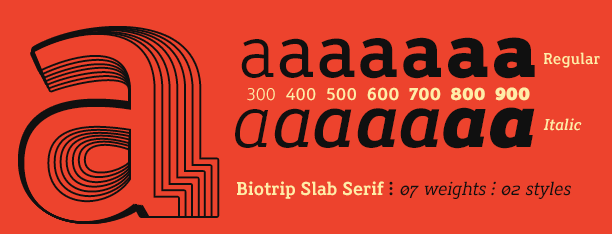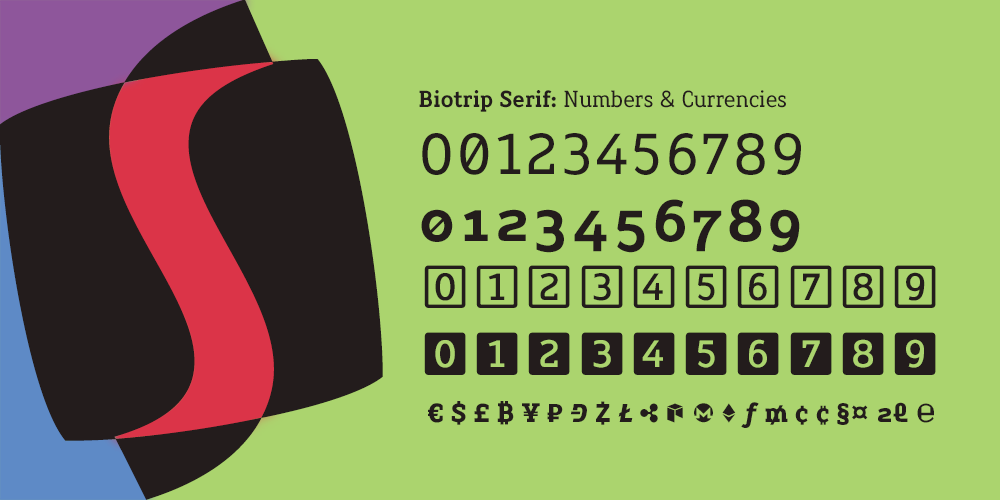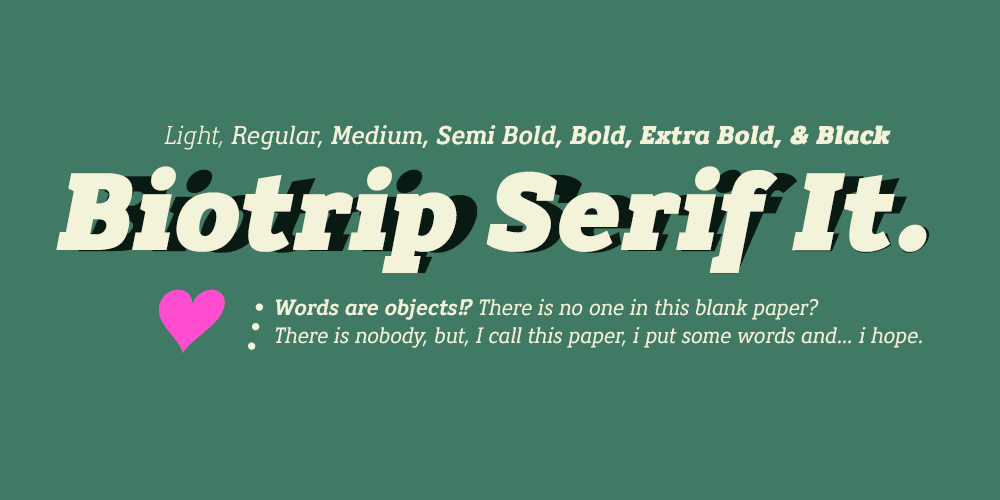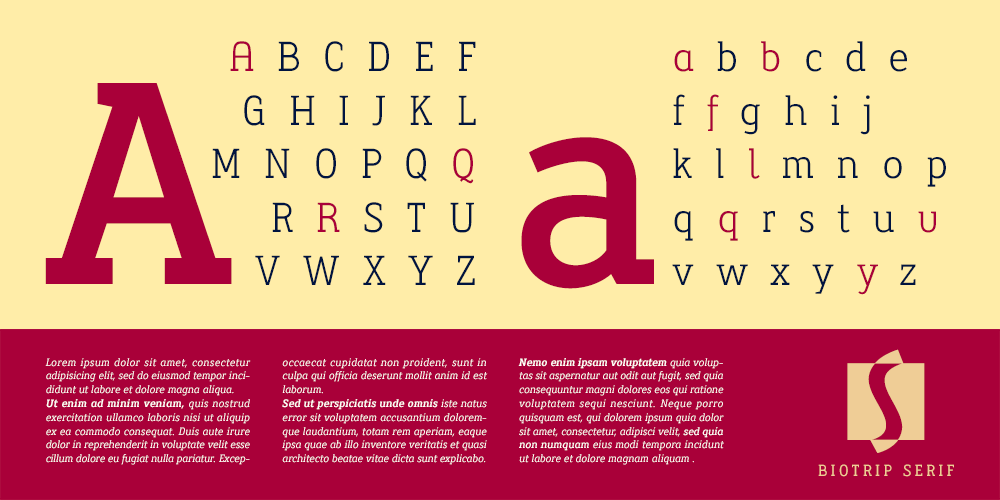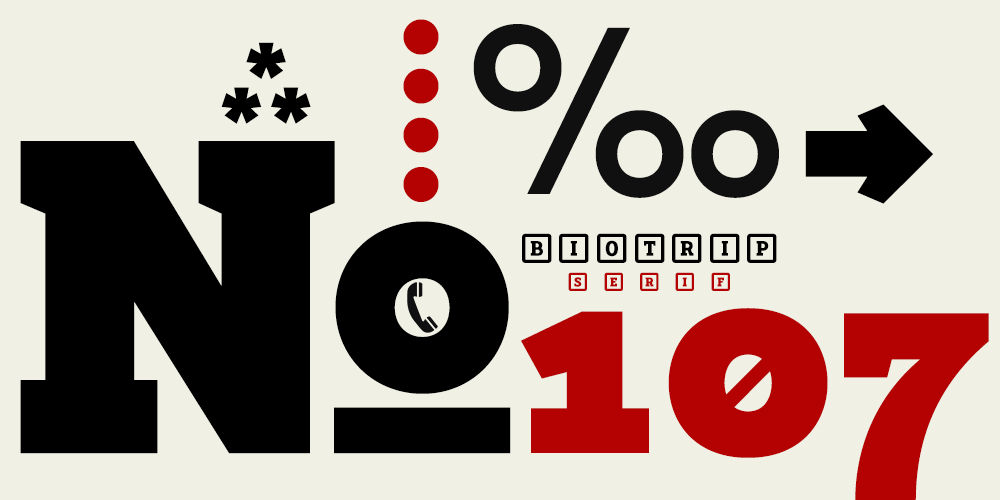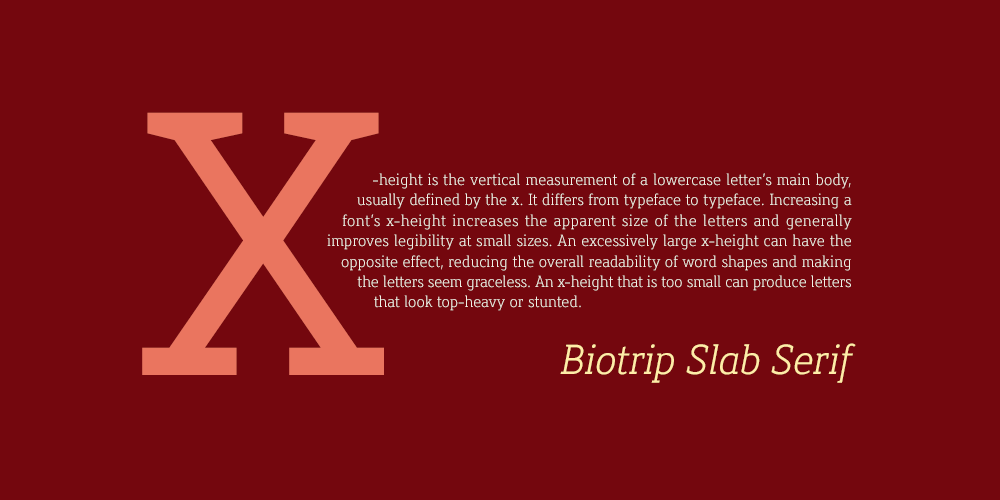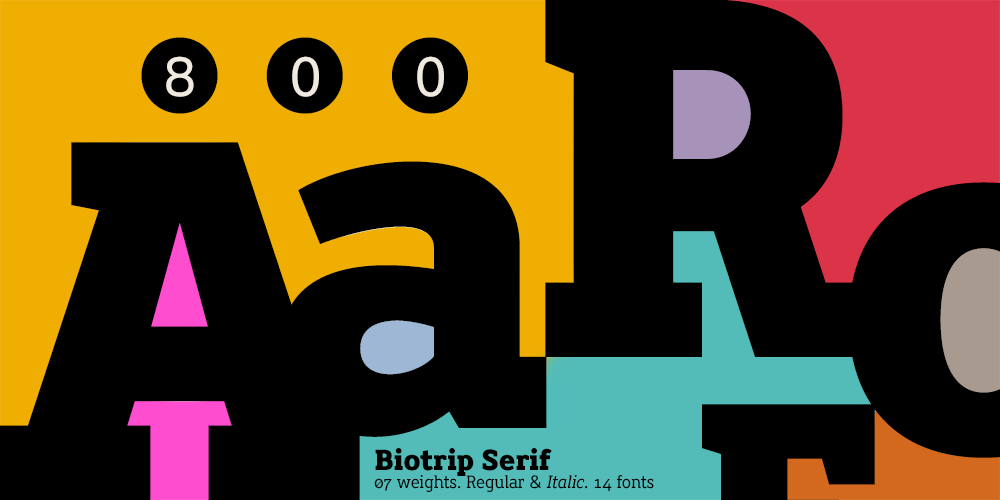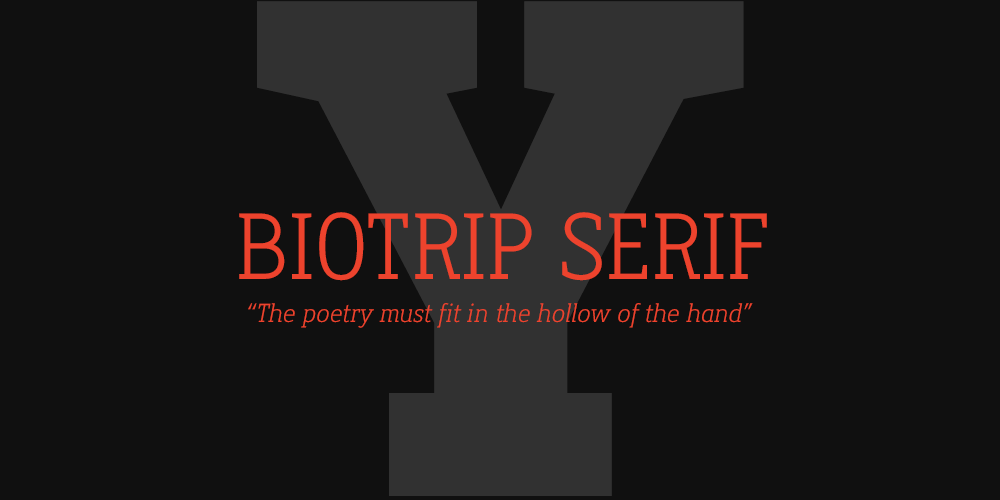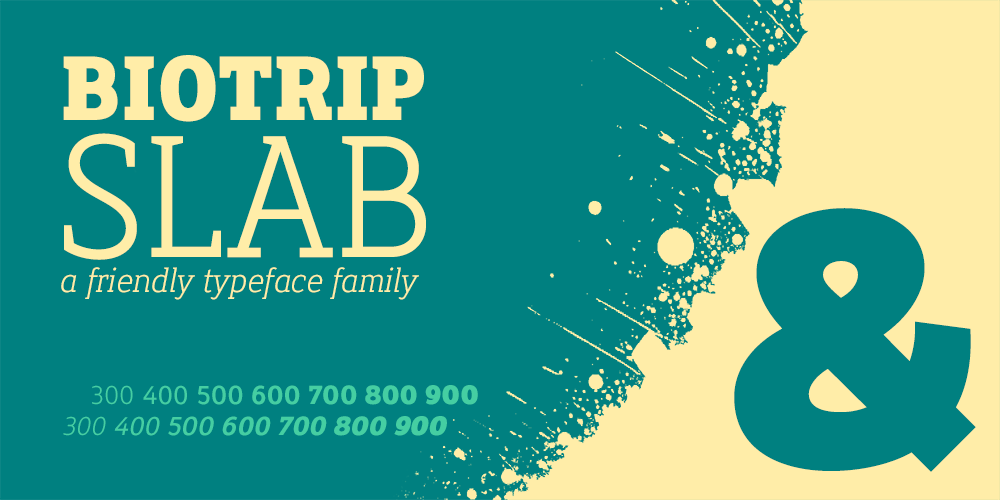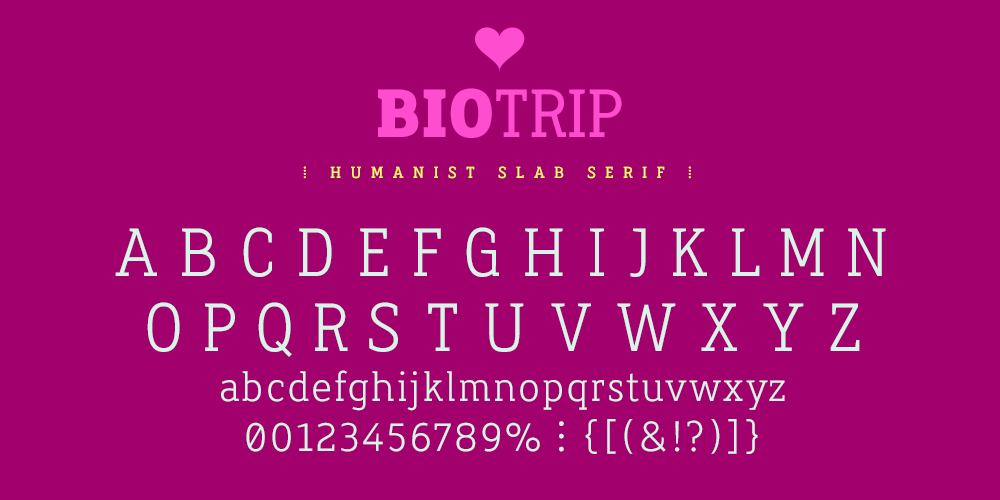
Estilo: Slab Serif, Display, Humanista, Editorial, Branding
Proporción: Light, Regular, Medium, Semi Bold, Bold, Extra Bold, Black
Alternates: 190
Autor: deFharo
Funciones OpenType: Additional languages, All Alternates, Alternate Annotation Forms, Bitcoin, Capital Spacing, Contextual Alternates, Denominators, Discretionary Ligatures, Fractions, Historical Forms, Inferiors, Kerning, Localized Forms, Numerators, Oldstyle Figures, Optical Size, Ordinals, Scientific Inferiors, Slashed Zero, Standard Ligatures, Stylistic Set, Subscript, Superior letters, Superiors, Superscript.
Regular & Italic | 792 glyphs | 14 fonts
Así surge Biotrip Serif, una extensión natural de mi universo Biotrip: una Slab Serif humanista y semi geométrica, con espíritu lapidario y raíces en las clásicas tipografías egipcias, reinterpretadas desde mi propia sensibilidad, añadiendo gravedad, textura y carácter sin perder la suavidad y humanidad del trazo original.
El Alma de las Slab Serif.
Biotrip Serif nace como una slab serif humanista, esa especie particular de tipografías que mezclan la geometría racional con la contundencia egipcia y la sensibilidad del trazo manual. Las Slab Serif tienen una historia fascinante, surgen en el siglo XIX durante la Revolución Industrial, estas fuentes de «serifas cuadradas» fueron diseñadas para impactar, para captar la atención en carteles y anuncios.
Las slab serif —ya sabes, esas letras con serifas cuadradas tan potentes que parecen diseñadas para no caerse jamás— son robustas, estables, directas. Son tipografías que dialogan entre la fuerza del bloque y la sofisticación del detalle. Pero esta familia va más allá: combina serifas cuadradas en la base —ese anclaje firme y contemporáneo— con serifas lapidarias en la parte superior, más ligeras y afiladas, que rompen la monotonía visual y guían la mirada con elegancia, creando un juego visual único que aporta ligereza, dinamismo, ritmo a cada palabra y refinamiento que oxigena la estructura slab tradicional. Es una dualidad perfecta: estabilidad en la raíz, dinamismo en la cima.
El resultado es una tipografía multipropósito hecha para la legibilidad y la expresividad. Aunque parte de una construcción geométrica, su modulación es orgánica, con trazos que evocan la escritura manual. Sus formas amables —ni frías ni mecánicas— establecen una relación honesta y cercana con el lector, convirtiéndola en una herramienta versátil y confiable.
La Familia Completa: Precisión y Expresión
Biotrip Serif está compuesta por 14 fuentes, distribuidas en 2 estilos (Regular e Itálica) y 7 pesos: Light, Regular, Medium, Semi Bold, Bold, Extra Bold y Black.
Una gama completa para construir jerarquías claras, sistemas visuales robustos y diseños con carácter, con toda la fuerza de una slab y toda la suavidad de un diseño humanista viviendo civilizadamente en la misma familia.
La familia incorpora un amplio repertorio tipográfico:
- 06 juegos completos de números para precisión editorial y técnica.
- 03 juegos de mayúsculas.
- 05 juegos de minúsculas para lograr matices tipográficos únicos.
- Rigor Técnico: Fracciones perfectas, fórmulas químicas o matemáticas impecables gracias a números posicionales, ordinales, denominadores, numeradores e inferiores científicos.
- Puntuación con Personalidad: La misma colección de signos decorativos únicos —asterism, therefore, because, tricolon, etc.— para dar un aire de erudición y distinción a tus textos.
- Formas Anotadas (Alternate Annotation Forms): Activa los estilos blackcircle o circlewhite para números y mayúsculas, ideales para anotaciones, listas o elementos de interfaz.
- Fluidez Inteligente: Ligaduras estándar y discrecionales, junto a alternativas contextuales para la puntuación, aseguran una textura de color perfecta y una lectura cómoda.
- Símbolos para la Era Global: Un set completo que abarca desde flechas direccionales hasta la iconografía monetaria internacional y de las principales criptomonedas.
- Idiomas: Latín Extended-A, para una cobertura lingüística amplia y profesional, porque el mundo es grande y no todo son acentos y eñes.
Carácter y propósito
Biotrip Serif está diseñada para ser multipropósito. Funciona con la elegancia de una tipografía editorial, pero también con la autoridad que exige una identidad corporativa sólida. Es igual de cómoda en un póster que en el packaging de un producto que pretende ser minimalista “pero cálido”, ya sabes, ese encargo que te llega cada dos semanas.
Su modulación orgánica, heredada del trazo manual, le permite mantener una legibilidad excepcional incluso en cuerpos pequeños, mientras que su estructura semi geométrica la mantiene precisa, estable, confiable. Es una tipografía que no solo se lee: se percibe. Sus formas amables incorporan calidez humana, alejándose de la frialdad geométrica para crear una conexión genuina con el lector. Es una tipografía diseñada para hablar con claridad, pero también con carácter; para ser robusta, pero no rígida; para ser elegante sin renunciar a su energía visual.
- Cartelería y Packaging que necesiten destacar con voz propia.
- Señalización y sistemas de información que requieran máxima legibilidad y personalidad.
- Logotipos con una base tipográfica robusta y distintiva.